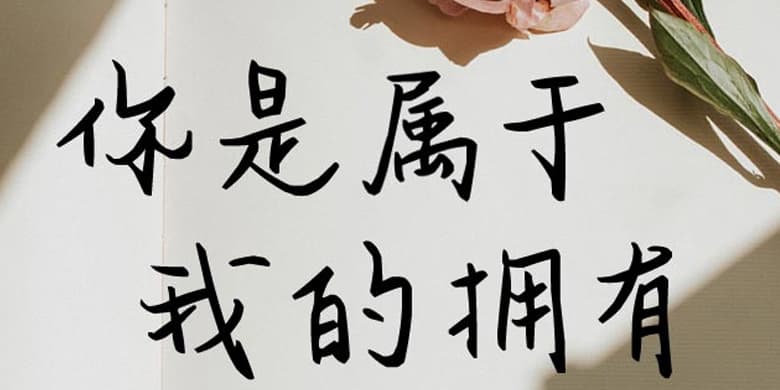
方正手迹-你是属于我的拥有
品牌:方正手迹设计师:余丹发行时间:2020字库编码:简繁扩展(GBK)分类:常规书写·硬笔字体属性:精品字
方正手迹-你是属于我的拥有
这款字打破常规笔画,将翘起的笔画作为行笔特色,拒绝平庸,给手写字添加了趣味。适用于少年儿童类的书刊、品牌广告和产品包装设计,以及社交网络的个性化用字。